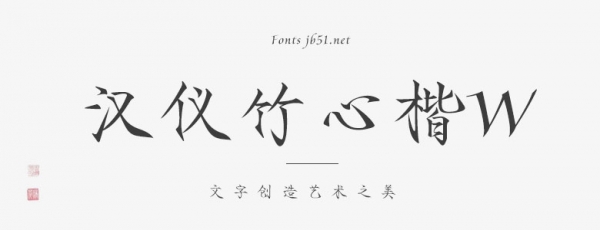
漢儀竹心楷是一款以瘦金體為藍(lán)本,融入了行書元素而形成的設(shè)計(jì)字體。字體整體呈現(xiàn)出很強(qiáng)的中式文化質(zhì)感,新派中式濃厚的同時(shí)強(qiáng)調(diào)古儀、靜雅、遒麗,宛如翩翩君子,散發(fā)出濃濃的書卷氣息。字形遵循瘦金體結(jié)構(gòu)并加以修改,使其中正規(guī)整;融入行書以增加書寫的灑脫、飄逸。適合于文化類的宣傳設(shè)計(jì)、商業(yè)類品牌的廣告和產(chǎn)品包裝設(shè)計(jì)以及個(gè)性化文字排版等較多場(chǎng)景。